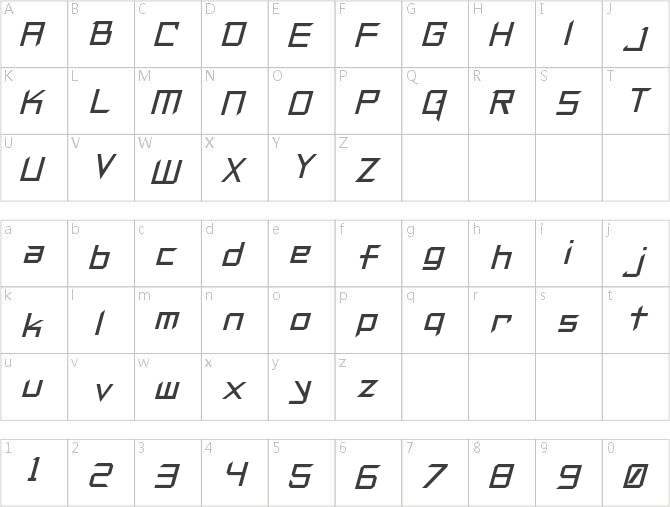
Furmanite Bold Italic 詳情頁(yè)
Furmanite Bold Italic字體字庫(kù)是一款讓人賞心悅目、百看不厭的英文字體,適合各類廣告和產(chǎn)品包裝設(shè)計(jì)應(yīng)用,字體大小0.02MB,格式為ttf字體,上傳用戶是錦程正陽(yáng),作者/版權(quán)方為未知